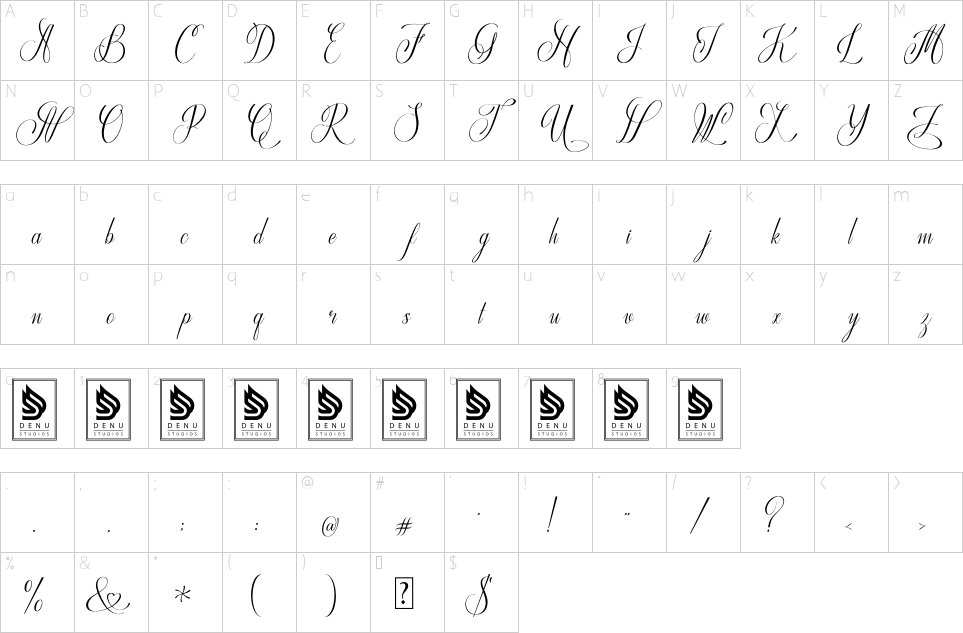
Descubra a frescura e a simplicidade do Defalliya Font, uma elegante escolha para designers gráficos e aficionados por letras. Desenvolvida pelo Denustudios, essa fonte lhe oferece um tom suave e harmonioso que é perfeito tanto para textos de design profissional quanto para o uso em aplicativos pessoais. Com sua aparência clean e minimalista, a Defalliya Font se destaca como uma opção ideal para criar elementos visuais modernos. Sujeitada à natureza da linguagem no Brasil e baseada nas características da grafia do português, essa fonte oferece um toque sofisticado que complementa perfeitamente qualquer projeto de design. Download o Defalliya Font em versões Windows e Mac para começar a explorar sua capacidade única. Com 432 downloads até o momento, é claro que esta fonte já conquistou muitos usuários apaixonados por seu estilo único e funcionalidade. Sinta-se à vontade para experimentá-la no seu próximo projeto!